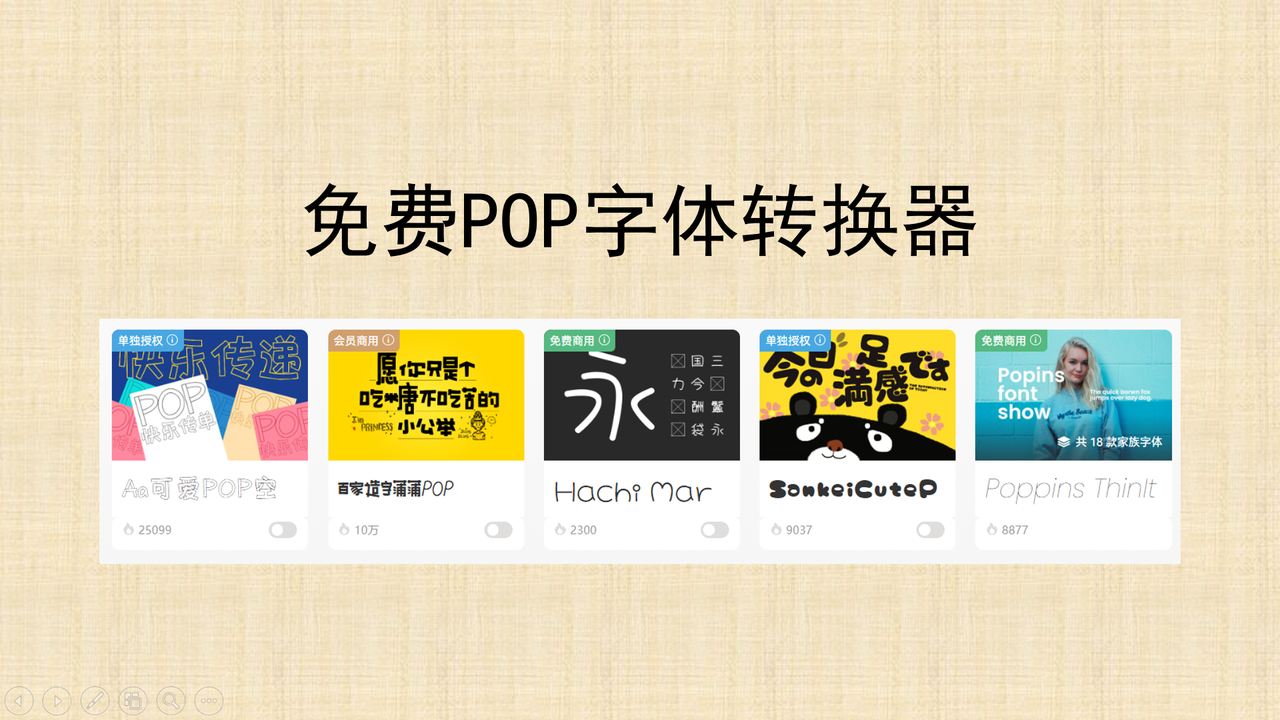
海报设计必备:免费 POP 字体转换器,在线生成艺术标题
POP 字体就是我们俗称的卖点广告,是一种专门为商业促销设计的手绘风格艺术字体,经常被用于海报设计的标题的选择,用来吸引客户的注意,激发客户的购买欲。怎么能快速获得 POP 字体呢?找到一个免费的 POP 字体转换器非常重要。今天整理 6 款免费的在线 POP 字体转换器,覆盖炫酷特效、霓虹灯风格、复古手写、涂鸦等多个风格,彻底解决“标题不吸睛”的问题。这些工具都不需要你掌握任何的设计技巧,可以一键将字体转换为 POP 字体,轻松提升海报设计的吸引力。
一、字由
字由是知名的国内字体管理工具,有海量字体资源,免费商用字体 3580+ 款,会员商用字体 580+ 款,单独授权字体 5000+ 款,并且会持续上线更新字体,满足多样化的设计需求。这样庞大的字体库,自然包含我们所需要的 POP 字体,用户可以根据风格类型对字体进行筛选,或者输入海报相关的标题,可以自行搜索适配的 POP 字体。字由最值得夸赞的一点就是,每款字体的左上方都标注了它的授权方式,字体版权清晰,让你用字无忧!
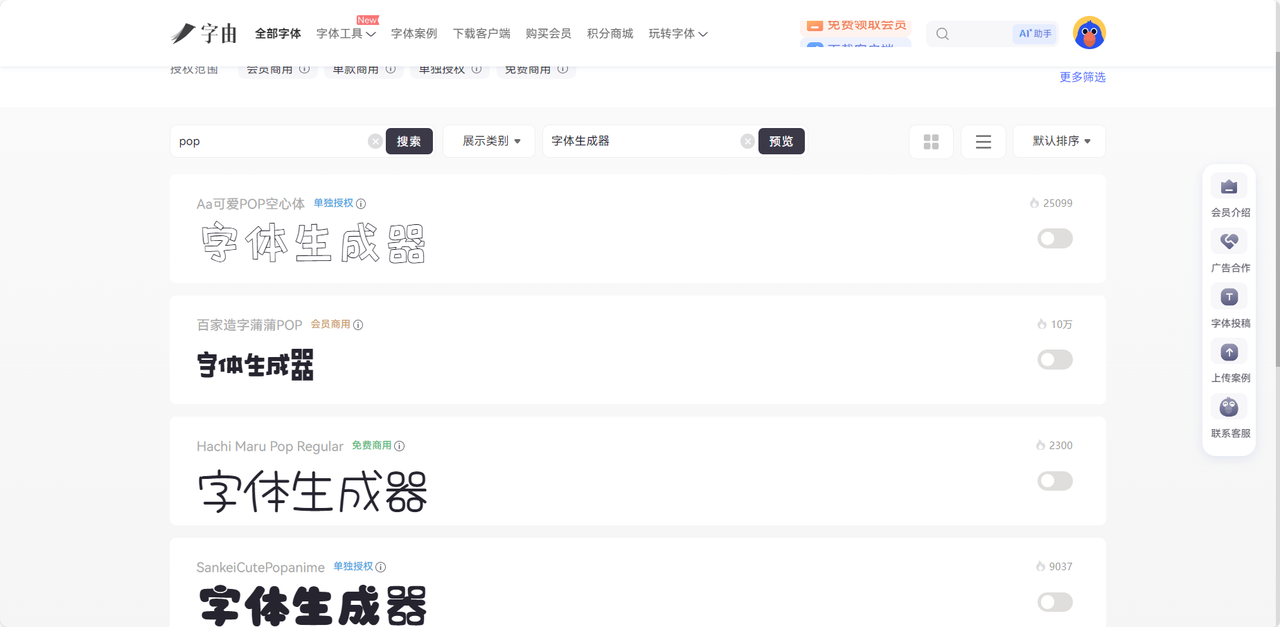
二、FontsPool
FontsPool 主打 POP 风格的艺术字转换与特效生成,是海外最受欢迎的免费POP字体工具之一。它拥有 120 + 款专业 POP 字体,每款字体都是设计师原创,免费且没有任何水印,完美适配标题、海报、社交文案等场景的设计需求。用户只需要输入文字即可秒级生成 POP 效果,支持中英文、数字、符号全字符转换,生僻字与特殊符号覆盖率达 98%,避免传统工具字符缺失的短板。
三、Cool Font Generator
Cool Font Generator 是免费的艺术字体生成器,适配 Instagram、TikTok、Twitter 等海外社交平台,海外博主经常用它来设计 POP 文案。与其他 POP 字体转换器相比,它基于 Unicode 编码技术,可以将普通文字转换为特殊符号化的 POP 字体,转换后的文字不是图片,而是可编辑、可复制的文本字符,无需下载字体文件,支持在所有社交平台、聊天软件、评论区直接粘贴,不会出现乱码或显示异常。最值得一提的是,Cool Font Generator 附带符号装饰功能,用户可以在转换后的字体前后添加星星、爱心、箭头、线条等 100 + 种装饰符号,一键美化排版,让文案更具设计感。
四、FontSpace
FontSpace 想必大家都不陌生,这是一款涵盖了复古漫画、手写涂鸦等经典类型的 POP 字体转换器,拥有上千种免费的POP字体可供选择。该平台的字体不仅免费,还清晰标注了授权方式,可商用字体含量高达 80% ,有效避免了可能发生的侵权问题是设计师们的必备的宝藏免费字体库。FontSpace 和 Cool Font Generator 有一点很像,它也不需要下载字体文件,你可以直接将生成的文字复制粘贴到其他社交平台或网页。同时,它也支持下载 PNG 透明背景,直接下载字体文件用于PS、Figma等设计软件,灵活适配流程。
五、OnlineWebFonts POP Converter
OnlineWebFonts POP Converter 是英国常用的专业字体工具,和上述工具不同,它不是生成 POP 字体的工具,是一个专注于字体文件格式转换的平台。且能保证无损转换,不会压缩画质,支持 TTF、OTF、WOFF、SVG 等全格式互转,非常适合设计师整理字库。最关键的是,它可以将已有的 POP 字体文件转换为电脑可安装、设计软件可用的格式,支持批量上传,一次性可转换多个字体文件,处理速度非常快。值得夸赞的就是这款工具对 POP 字体的还原程度极高,不会出现任何笔画变形或是结构丢失的问题。同时还能提供字体子集化功能,能剔除无用字符,减小文件的体积,有效避免电脑卡顿。对于需要长期使用POP字体的设计师来说,它绝对是一个最佳选择,无需登录,全程免费。
POP 字体经常被用于零售业,或者是社团招募、校园宣传、手账装饰,最早制作 POP 字体的最简单的方法是手绘。但这个过程非常复杂且浪费时间,随着科技进步,才逐渐有了我们所说 POP 字体转换器,在线就能一键生成艺术标题。以上介绍的这些字体转换器大部分都可以支持商用,我建议大家可以多多尝试,因为每款工具都有它最擅长的部分,找到适配你的工具才是最重要的。